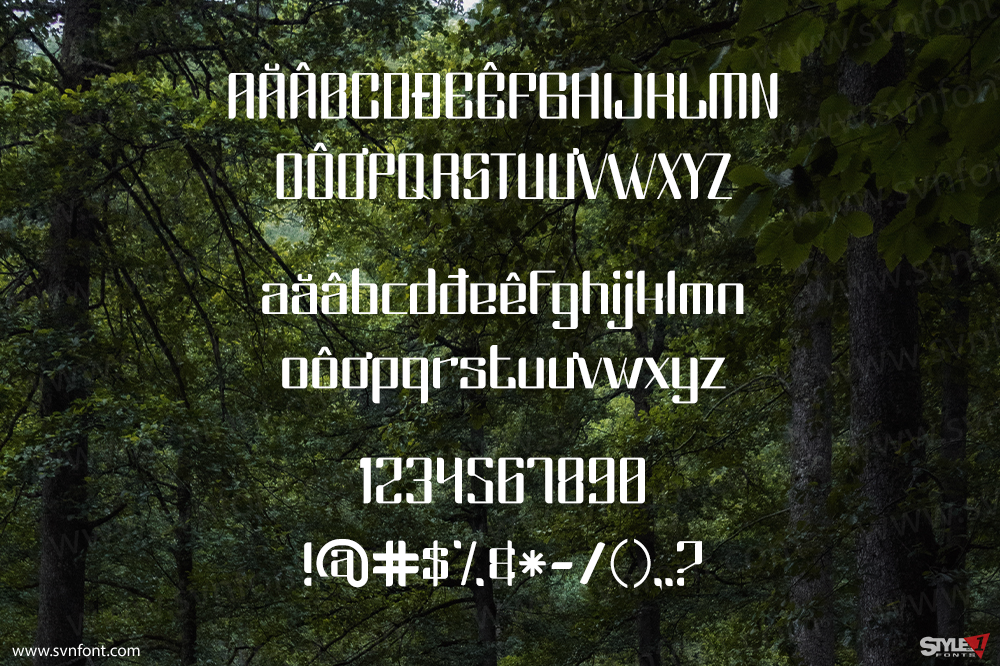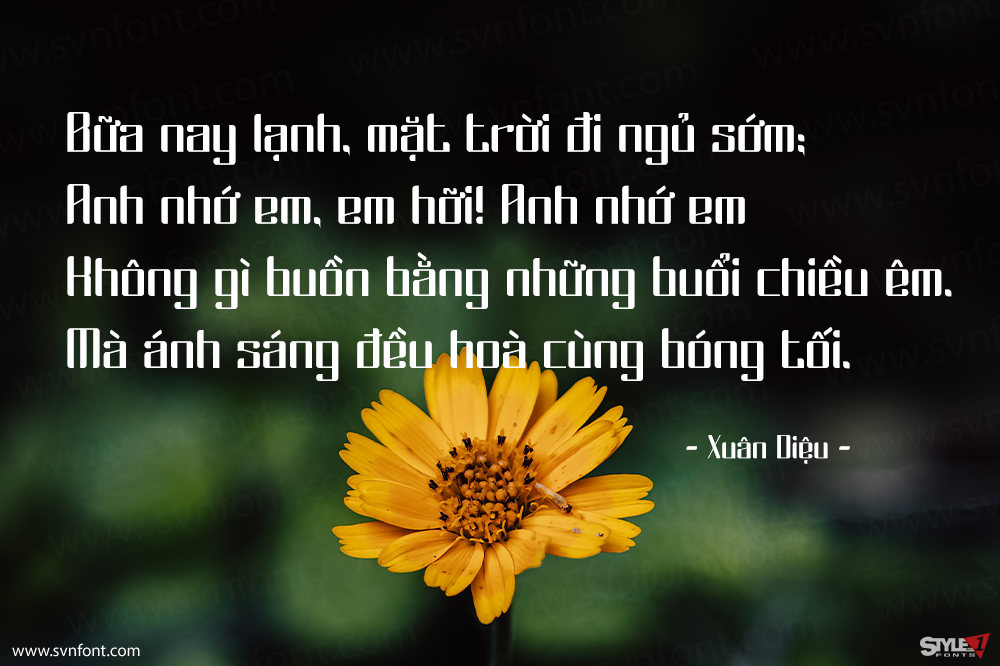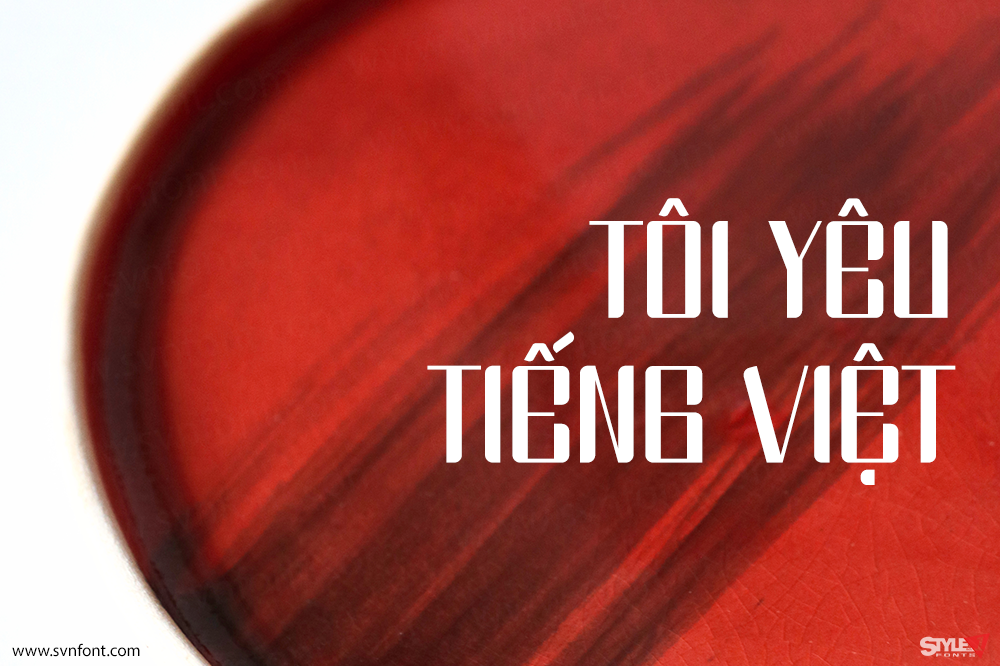
Crosver Font là một phông chữ hiển thị đậm nét và chân thực. Phông chữ này phù hợp cho mọi dự án xây dựng thương hiệu như logo, in áo thun, thể thao điện tử và nhiều hơn nữa. Nó nổi bật trong nhiều ngữ cảnh khác nhau.
Nhà thiết kế: Maiko Hatta
Nhà phát hành: Maiko Hatta